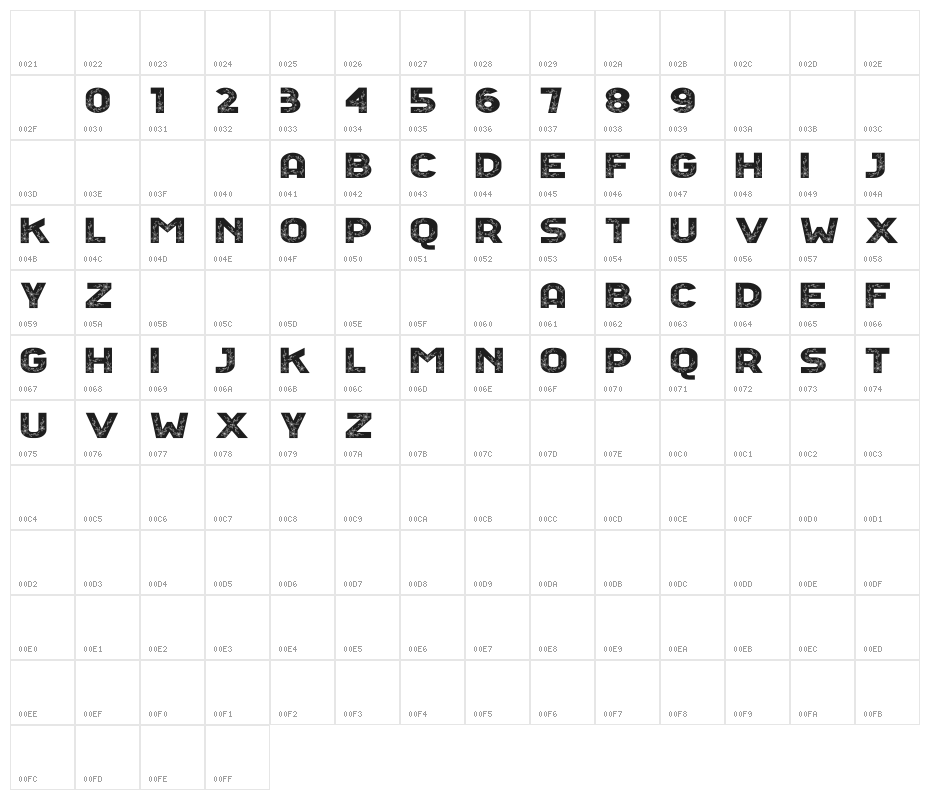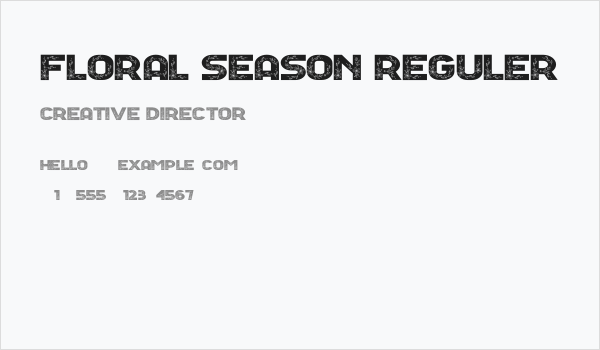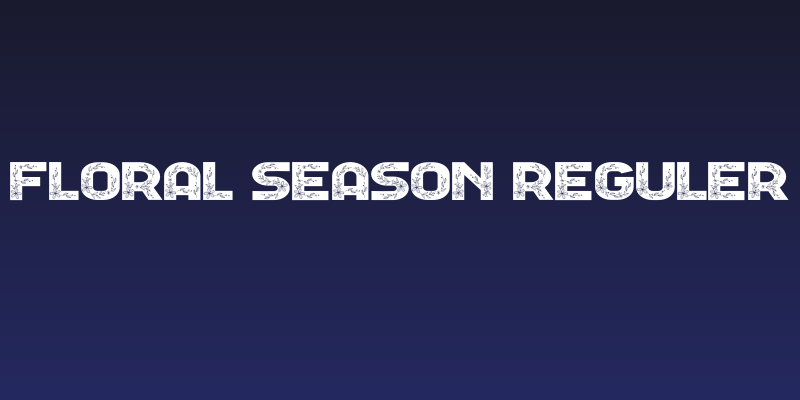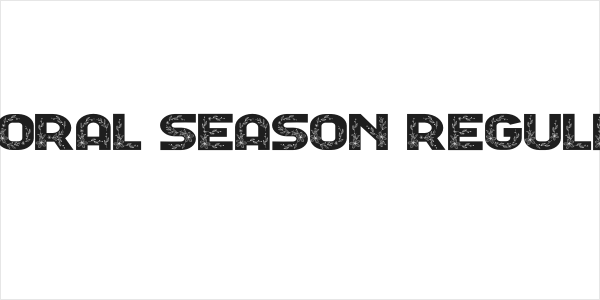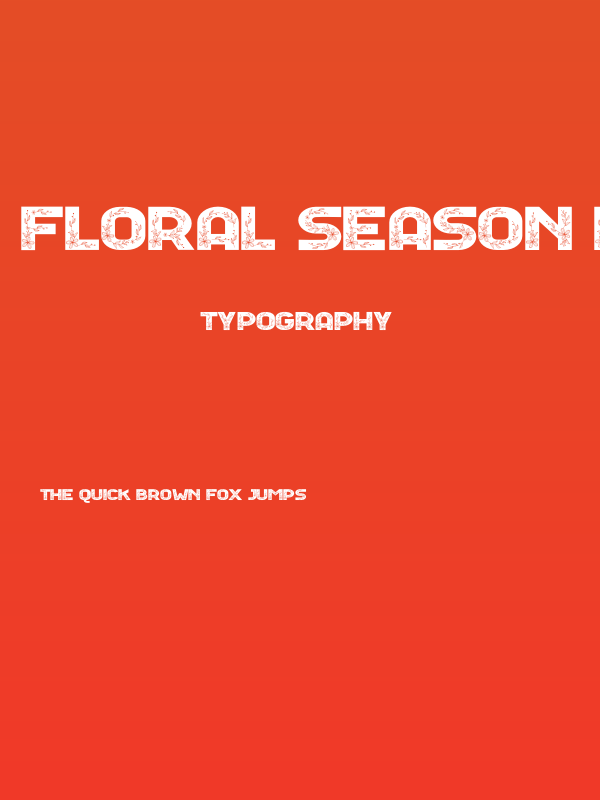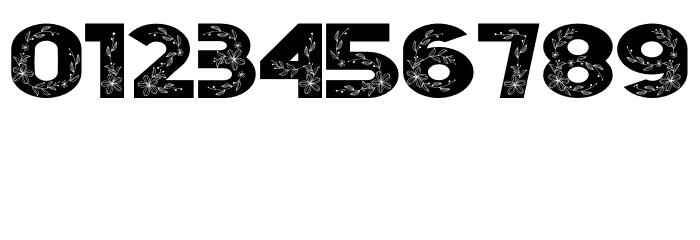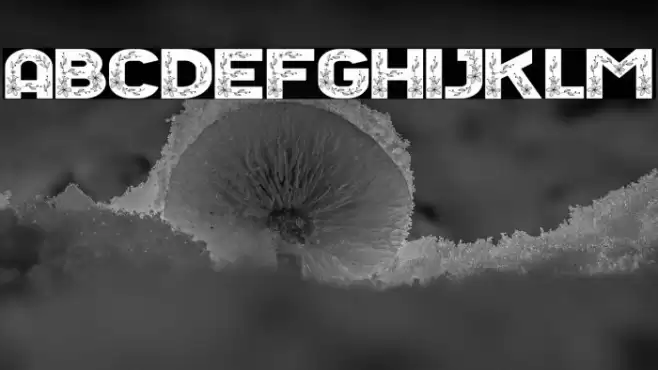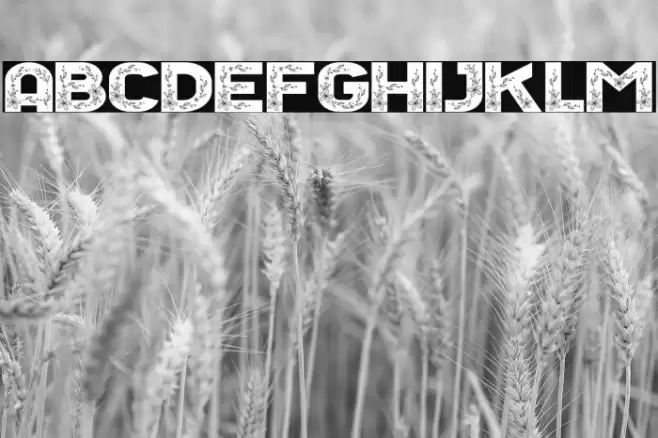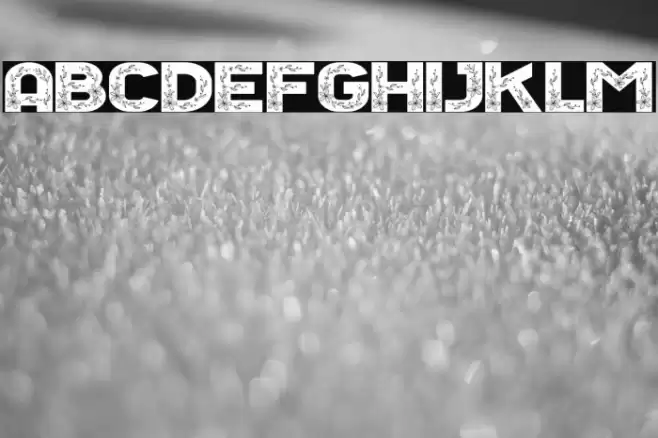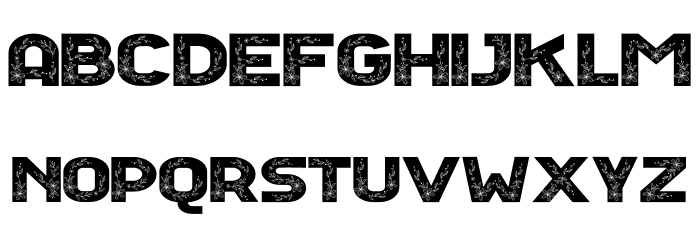
Floral Season Reguler Font
| おすすめプロジェクト | Ideal for wedding invitations, event posters, branding, and artistic projects requiring a decorative touch. |